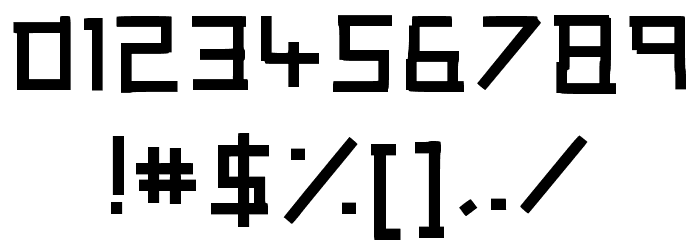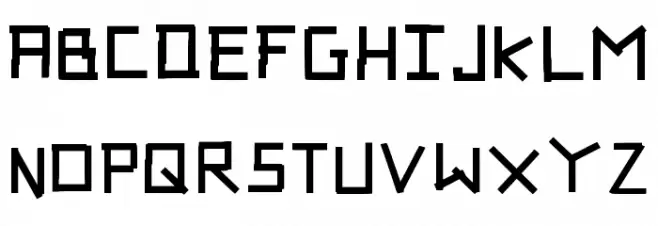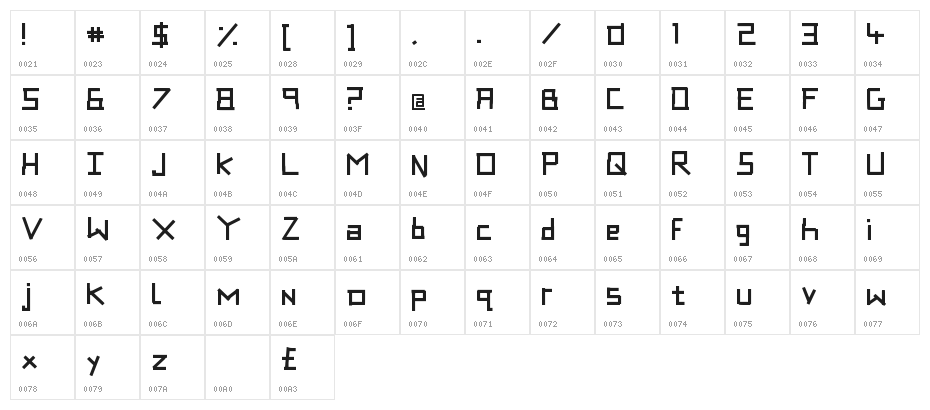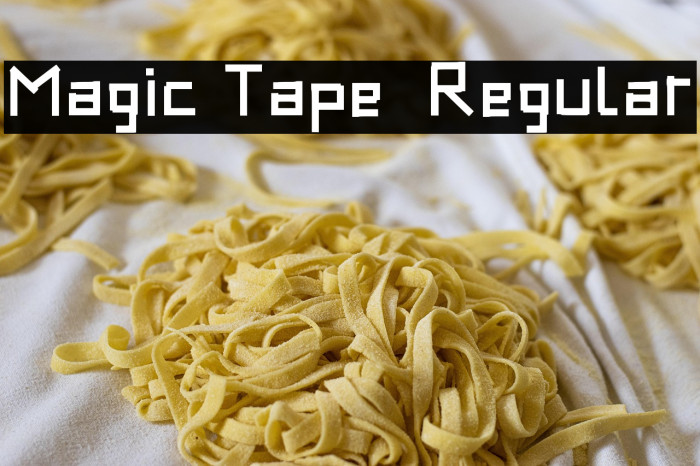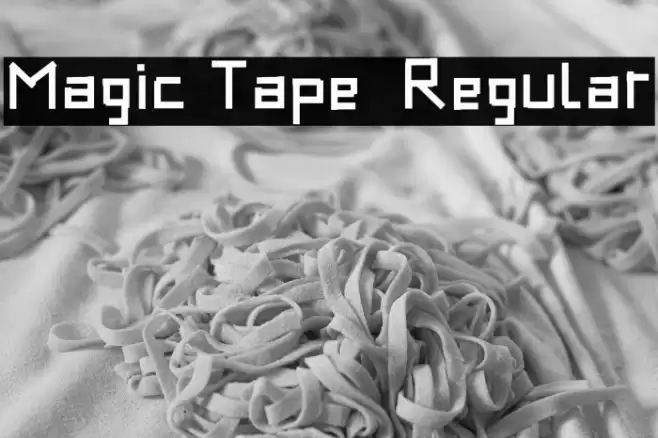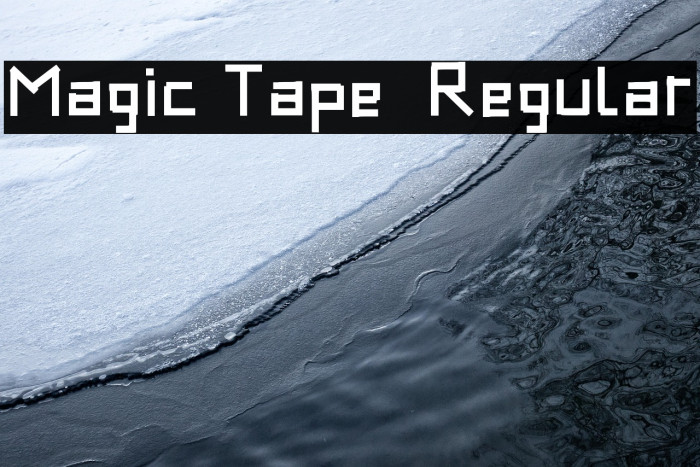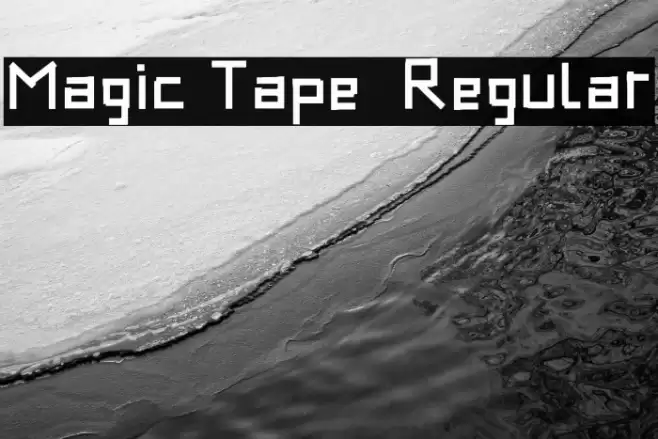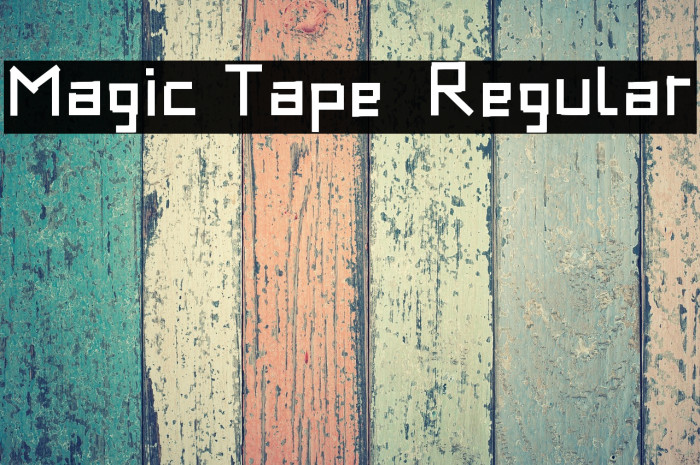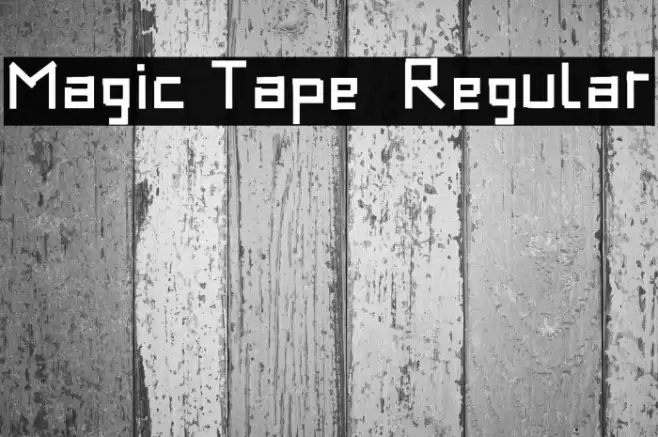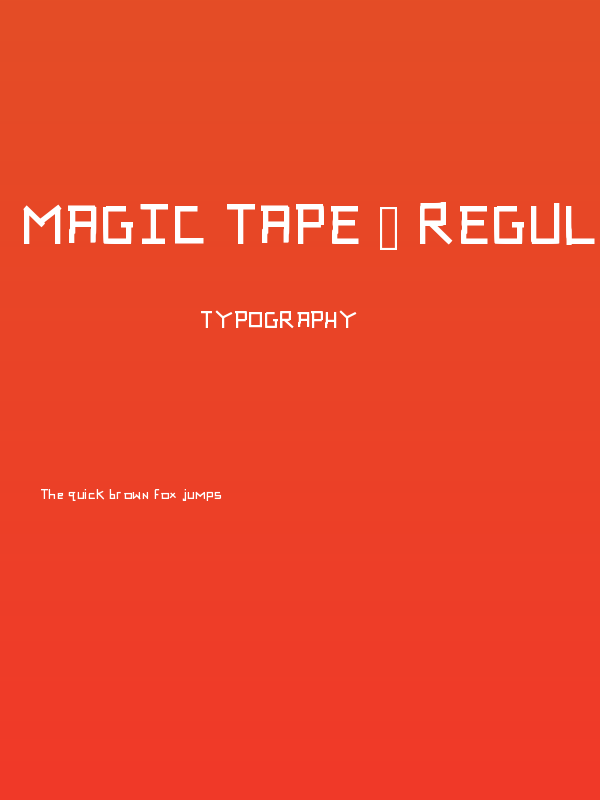
Magic Tape - Regular Font
✎ Thick
| 字体家族 | Magic Tape |
| 分类 | Thick |
| 推荐项目 | Ideal for digital art, video game graphics, posters, and branding that requires a modern, edgy look. |